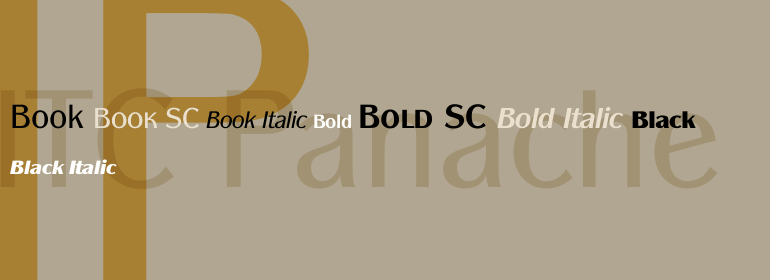
ITC Panache®
和其他大多数艺术作品一样,字体为我们提供了一个了解作者个性和情感的窗口。ITC Panache不仅提供了这个窗口,它的名字也很贴切。ITC Panache的创始人Edward Benguiat先生在设计中富有活力和创造力,Ed Benguiat设计了数百种令人兴奋和流行的字体。
Benguiat的设计目标是创建一种多功能、实用和独特的无衬线字体。我们认为他的成功令人钦佩。ITC Panache的三种字重搭配得非常好,可以互相补充,或者在必要时提供强调。在文本大小和设计微调的广泛测试中产生了一个字体家族,该家族非常均匀且颜色一致。在ITC Panache中设置的文本很吸引人。它非常容易阅读,即使在长文本块或小字号上。
当设置在更大的尺寸或用于标题时,ITC Panache的性格特征对读者来说变得更加明显。它们有助于创建具有特色和风格的图形。大或小。一点或很多。很难不使用ITC的Panache。
如果你将ITC Panache归类,它可能会被归类为无衬线体,但这并不能完全描述该设计,也不能完全符合该设计。笔画粗细有轻微的对比,随着字重的增加,该差异变得更加明显。但ITC Panache与其他无衬线体还有很多区别,也许最明显的是它的高腰和相应的“圆形”,这两个特征使ITC Panache与感性联系在一起。相反,在Cloister和ITC Berkeley Old Style等字体设计中典型的老式 "e",以及在20世纪初无衬线字体设计中常见的"g"。大写字母“A”甚至有Caslon设计的杯型上衣。ITC Panache的美丽之处在于,所有这些看似毫不相关的设计特点,都融合在了一个非凡的连续性设计中。”
Typefaces, like most other works of art, provide a small window into the personalities and sensibilities of the artists who create them. ITC Panache not only provides this window, it is also aptly named. Mr. Edward Benguiat the dreator of ITC Panache, has all the dash, verve (and panache) hinted at in the design, Creative, capable and prolific, Ed Benguiat has drawn hundreds of exciting and popular typeface designs.
Benguiat's design goal was to create a sans serif typestyle that is versatile, utilitarian - and distinctive. We think he has succeeded admirably. ITC Panache's three weights mix exceptionally well to complement each other or provide emphasis where necessary. Extensive testing at text sizes and design fine-tuning has produced a typeface family which is remarkably homogenous and consistent in color. Text set in ITC Panache is inviting without dissapointment. It is exceptionally easy to read, even in long text blocks of copy or small point sizes.
When set in larger sizes or used for headlines, ITC Panache's character traits becomes more apparent and pronounced to the reader. They help to create graphics with distinction and style. Big or small. a little or a lot. it's hard not to use ITC Panache well.
If you could pigeonhole ITC Panache, it would probably be classified as a stressed sans", but this would not completely describe, or do justiceto, the design. There is a slight contrast in stroke weight, which becomes more pronounced as the familiy weight increases; but there is a more to distinguish ITC Panache from ather sans serifs. Perhaps most obvious is its high waist and correspondingly slight condensation of the top half of the "round" capitals. Both of these traits link ITC Panache with the sensuous forms of art nouveau creations. In contrast are the typicall old style "e" found in designs like Cloister and ITC Berkeley Old Style, and the two storied "g" common to the early 20th century sans serif designs. The capital "A" even has the cupped top found in Caslon designs. Part of the beauty of ITC Panache is that all of these seemingly unrelated desig traits are melded into a design of exceptional continuity."